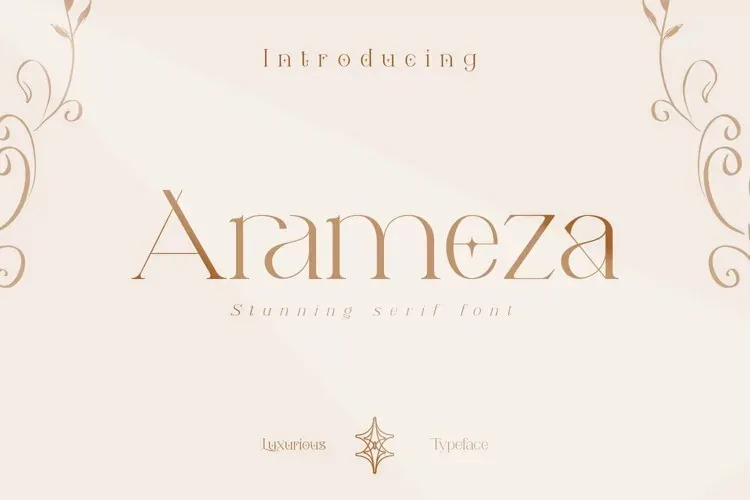
Arameza Font é uma elegante fonte serif criada por Irfan Hidayat, conhecida pela sua versatilidade para uma ampla gama de propósitos de design. O que torna esta fonte ainda mais interessante são as ligaturas presentes nela, que proporcionam um sentimento nostálgico e sofisticado em uma aparência moderna e contemporânea. Esta característica única também oferece um toque luxuoso a cada caractere, criando valor adicional para qualquer projeto de design, seja eleve um projeto de banner ou invitação, escreva textos para web sites, crie cartões de visita ou embalagens. Além disso, esta fonte suporta vários idiomas, tornando-a uma opção indispensável para profissionais e designers em todo o mundo.